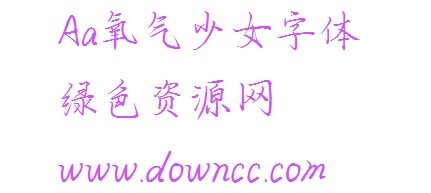
aa氧氣少女字體也叫aa星玥體,是一款書寫大方、運(yùn)筆流暢的手寫字體,給人清晰娟秀的視覺效果,造型端正筆觸有力,喜歡就來綠色資源網(wǎng)試試吧!
氧氣少女體有著柔和的筆觸,用筆簡(jiǎn)潔不拖沓,行筆流暢而不尖銳,給人十分舒適的藝術(shù)呈現(xiàn),可以廣泛運(yùn)用在平面設(shè)計(jì)、海報(bào)設(shè)計(jì)、創(chuàng)意策劃等場(chǎng)合。
Aa氧氣少女字體即Aa星玥體!